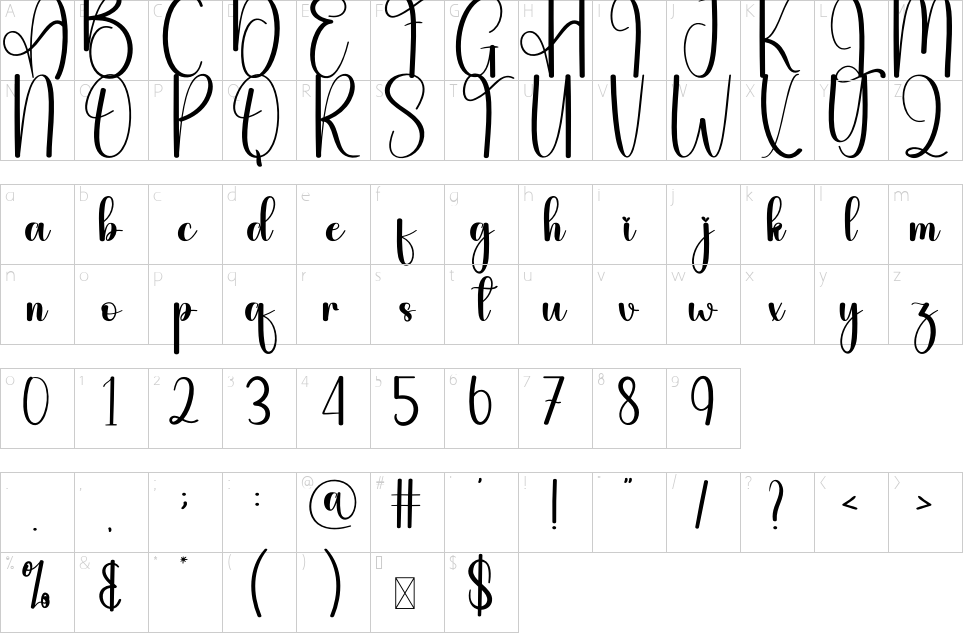
Aqui está uma descrição em português, envolvente e natural, para uma página de download da fonte ‘Moon Font | 1001 Free Fonts’: Moon Font é uma elegante e sofisticada fonte gráfica que traz uma leve luminosidade ao seu design. Confeccionada por William Jhordy, esta fonte oferece um ar de tranquilidade e frescor, perfeita para criar texturas e efeitos modernos. Com seu design minimalista e versátil, Moon Font é perfeito para gráficos digitais, design gráfico e publicidade digital. Esta fonte é uma excelente adição para qualquer projeto visual que busque trazer uma atmosfera suave e alegre. Foi baixada pelo menos 154 vezes, demonstrando seu valor e popularidade. Adquira seu próprio exemplar agora e experimente a sofisticada harmonia de Moon Font.